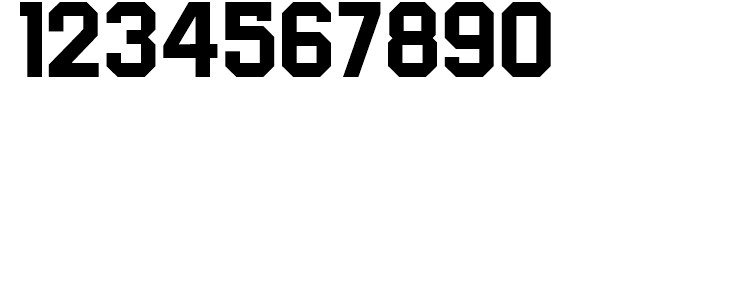
Suche spezielle Blockschrift
kennt jemand die Schriftart der Beispielgrafik?
Die Schrift wird häufig bei Ziffern für Fußball-Trikots verwendet.
Die hat noch eine Outline, aber das Innenleben sieht so aus wie deine gesuchte.
Jene ist formal auch so aufgebaut, aber in Details unterschiedlich:
Es wird aber zig weitere sehr ähnliche geben, "College" wäre ein geeignetes Stichwort für die Suche.